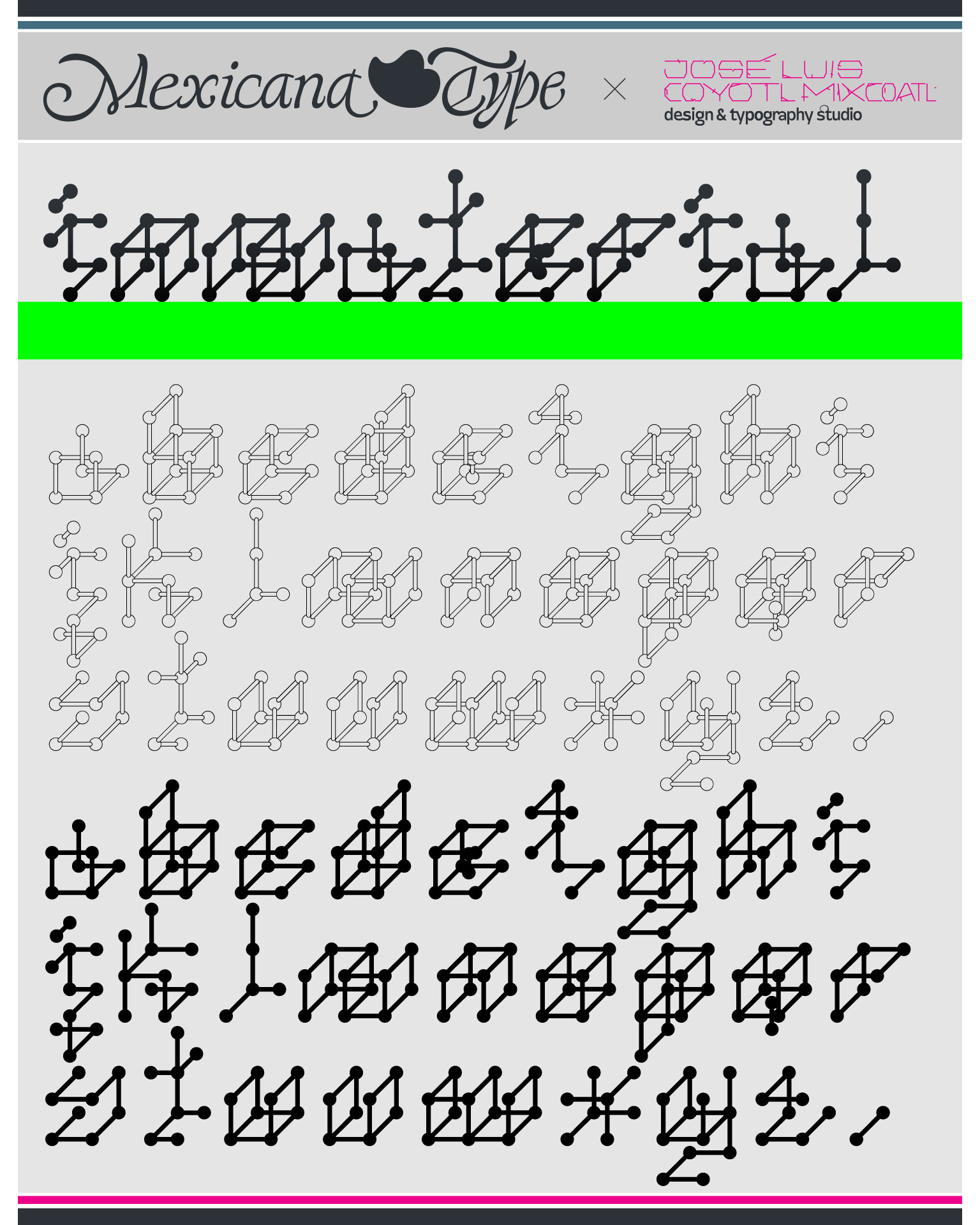
MxT Inmaterial fue creada a partir de hacer un juego de una estructura modular de planos que se enlazan bajo el principio de representaciones gráficas de química básica, modulada dentro de una retícula isométrica de un cubo y puntos de enlace esféricos y líneas que se conectan entre si formando cada caracter para generar una sensación de profundidad, Si bien sus combinaciones la hacen una tipografía difícil de leer, sus atributos van mas allá de la lectura y más en el sentido de experimentación con una lúdica visual muy singular.